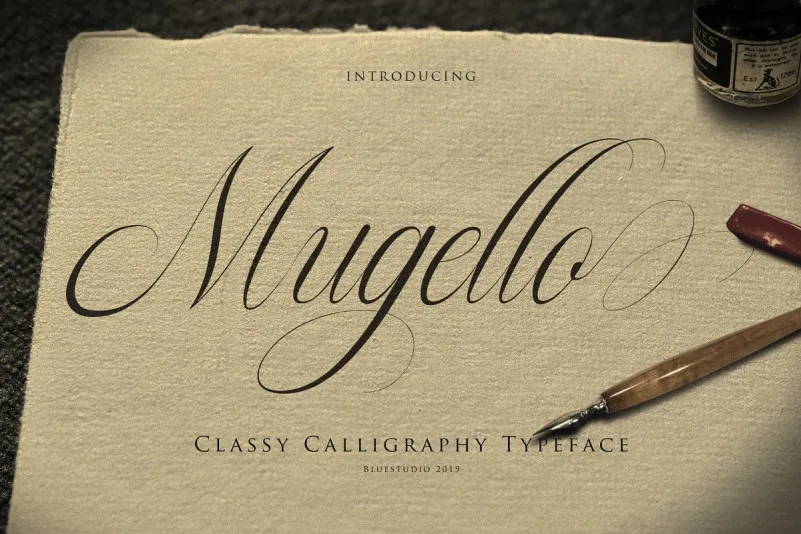
Mugello Classy Calligraphy Font – Download Grátis
Esta é uma nova fonte calligrafia que oferece um toque fresco e natural. Introduzimos a Mugello Calligraphy Font, criada pelo designer Bluestudio. Através de sua elegância moderna e limpa, esta fonte é perfeita para todos os seus projetos de design. É uma escolha ideal para criações como logos, marcas, capas, cartazes, revistas, convites de casamento, cartões de felicitação, citações e muito mais. Sua simplicidade e elegância tornam-a uma opção perfeita tanto para iniciantes quanto para designers experientes que procuram uma fonte calligrafia moderna e sofisticada. Se você busca um touch único e limpo para seus projetos de design, a Mugello Calligraphy Font é uma excelente escolha.